欧文書体の魅力がたっぷり! ジャンル別にわかる、モリサワ新書体2022【欧文編】
いきなりですが、質問です。欧文書体、どんな風に選んでいますか?元からパソコンに入っている書体で十分という方から、海外の情報を積極的にキャッチしている方まで、いろんな方がいらっしゃると思います。
モリサワでは近年、コンテンツのグローバル化のニーズを考慮して欧文書体ラインナップの充実にも力を入れています。 今年の欧文新書体はなんと、49ファミリー504書体という過去に例を見ないボリュームでリリース予定です。
この記事では、少しでも欧文書体のイメージを掴みやすくするための手がかりとして “ざっくり4つのジャンル” にわけてご紹介します。
和文同様に様々なデザインがあり、それぞれに合った使用シーンがある欧文書体の魅力をお伝えしていきますので、最後までお見逃しなく!
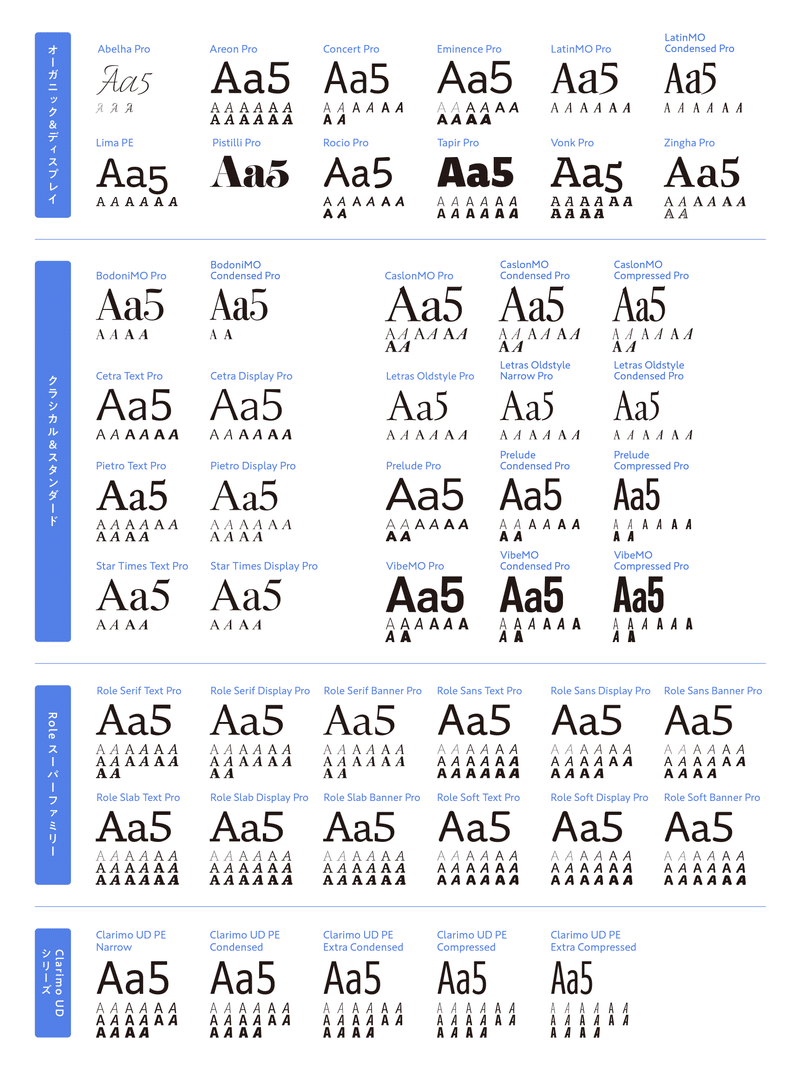
今年の欧文新書体を並べてみました。目を引く華やかな見出し書体からベーシックな書体まで、CondensedやCompressedなどの幅展開を含めるとこんなにたくさん……!
「Abelha Pro」や「Areon Pro」などのモリサワ タイプデザインコンペティションでの入賞作品や、アメリカで先行発売していた「Roleスーパーファミリー」も一挙リリースとなります。
ということで、ここからは個別の書体を詳しく見ていきましょう!
1. オーガニック&ディスプレイ
有機的なスタイルや、 見出し用途の強いインパクトを持つ書体をまとめたのが「オーガニック&ディスプレイ」。
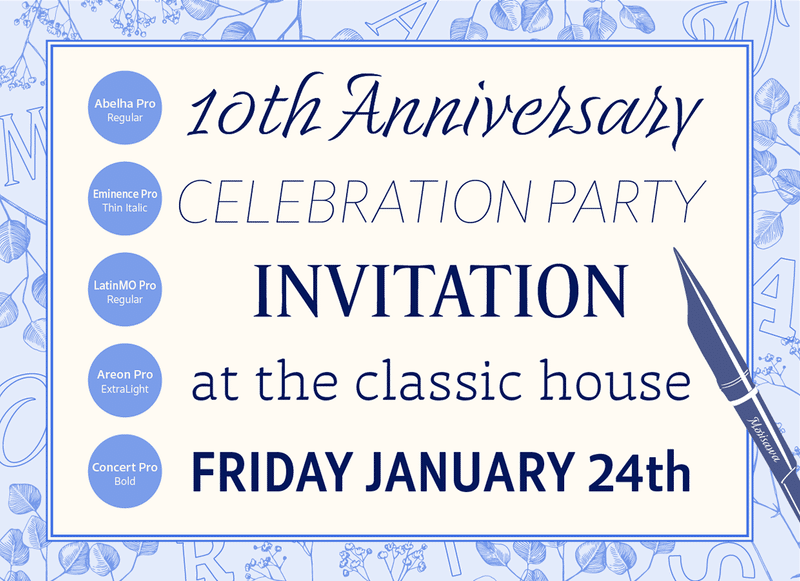
書体数が多いので、前後半に分けて画像にまとめてみました。
前半分は招待状をイメージしたワードで組んでいます!ほどよく丁寧でありながら、あたたかみも感じる書体が揃っています。
Abelha Pro
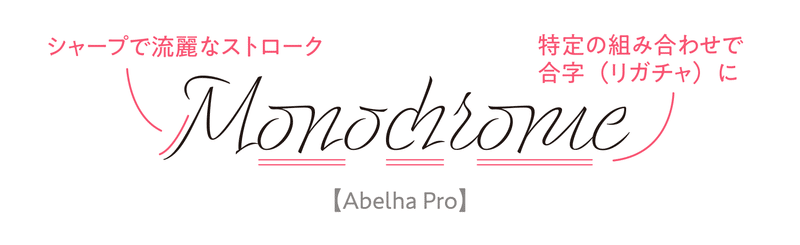
「Abelha Pro」は、書簡の筆跡を参考にデザインされたフォーマルな印象のスクリプト体です。シャープで流麗なストロークは、上品でありながらも軽やかな印象を与えます。
特定の組み合わせが来た際に置き換えとなる合字(リガチャ)にオリジナリティがあり、画像内「o・n」「c・h」「o・m」の組み合わせなどは、手書きだからこその合字だなと思います。
代替字形(オルタネイト)も多数搭載しているので、OpenType機能を使ってぜひお手元でいろんなパターンを試してみてください!
Areon Pro
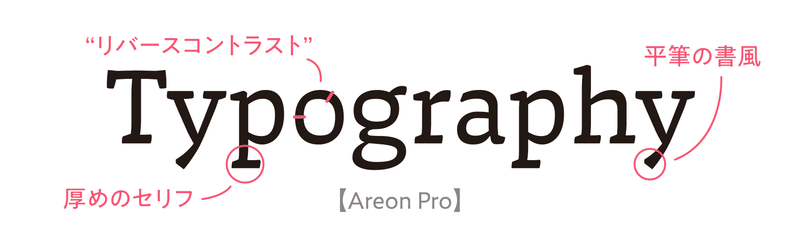
「Areon Pro」は、平筆の書風から着想を得た現代風のセリフ体です。“平筆の書風” というのは、例えば「y」の終筆に見られるような、平筆で書いた時の筆の角度によって太さが変わっているデザインのことを指しています。
セリフが厚めに設計されていることと、ややリバースぎみのコントラスト(太く描かれる部分と細く描かれる部分の関係性が逆転するデザイン)をもつことで、セリフ体でありながらどこか親しみやすさも感じます。
Concert Pro
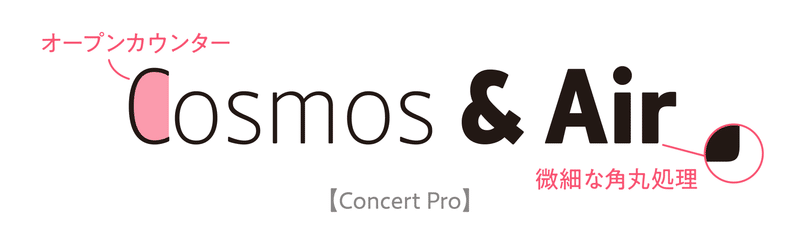
「Concert Pro」は、オンスクリーンでの利用を想定し開発されたやや長体ぎみのヒューマニスト・サンセリフ体です。
オープンカウンター(「C」などに見られる、文字の中に含まれる空間が開けていること)でシンプルな骨格であることに加え、ゆったりとしたスペーシングで設計されているため、可読性が高くなってます。
字幅の差が少なく文章を組んだ時に整理された印象をうけますが、アウトラインの先端に微細な角丸処理を施しているため、適度にあたたかみのある印象を与えることができる書体です。
Eminence Pro
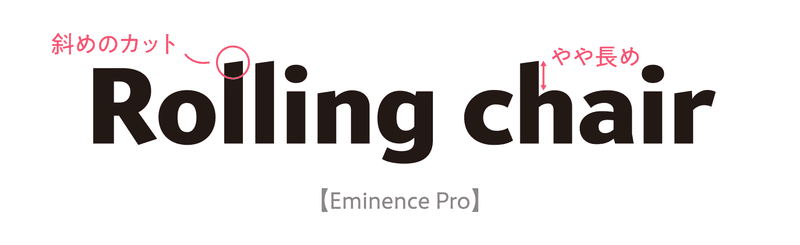
「Eminence Pro」はクリーンで明るい印象のサンセリフ体です。やや長めに設計されたアセンダー・ディセンダーラインが上品な印象を与えます。
画像内「l」(小文字のエル)の始筆に見られるような斜めのカットも特徴で、文章を組んだ際に心地よいリズム感が生まれます。ウエイトが上がるにつれカットの表情も色濃くなるので、細いウエイトで文章組みをし、太いウエイトを見出しで使った際にもしっかりメリハリを出すことができちゃいます!
LatinMO Pro / LatinMO Condensed Pro
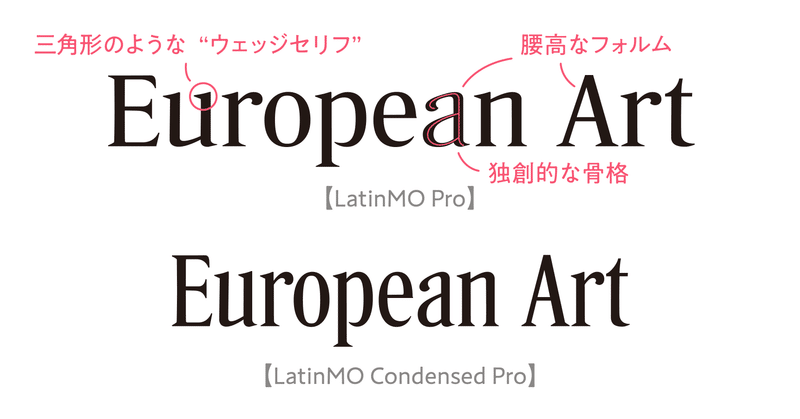
主に19世紀に見られた伝統的なウェッジセリフ体を再解釈したのが「LatinMO Pro」です。通常の字幅に加え、見出し利用に最適な長体のCondensedも用意されています。
“ウェッジセリフ” というのはなんぞや……という説明をしておきますと、“セリフ” というのは先端についた飾りのことで、それが三角形のような要素で構成されているのがウェッジセリフです。
この鋭利で繊細なセリフに腰高で独創的な骨格を合わせており、どこか気高さを感じさせるようなデザインになっています。伝記や歴史小説などの書籍装丁に合いそうな書体です。
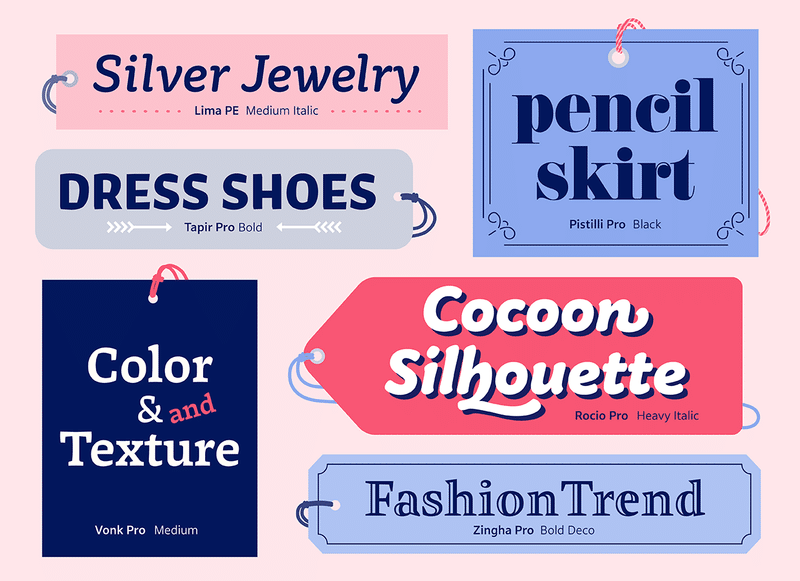
「オーガニック&ディスプレイ」の後半の書体たちを、ファッションをイメージしたワードで組んでみました!
デザイン性が高い書体が多く、和文組版のワンポイントアクセントとしてご利用いただくと華やかなニュアンスを演出できます。
Lima PE
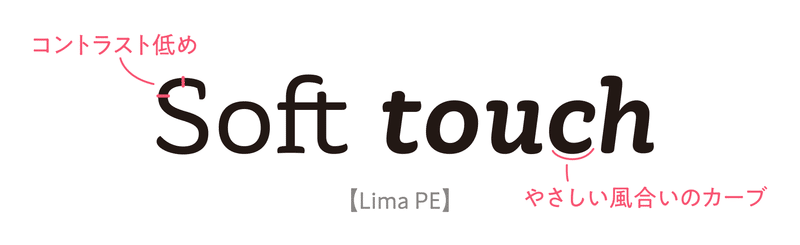
あたたかみのあるカジュアルな印象のセリフ体が「Lima PE」。
オンスクリーンの使用を想定して設計されており、アパーチャー(「S」や「c」などの文字の開口部)が広いことに加え、コントラストが低いので小さなサイズで使っても文字の輪郭が捉えやすく、本文組でも読みやすい書体です。
「c」に見られるような手書き由来のやわらかなカーブも、この書体のエッセンスになっています。
Pistilli Pro
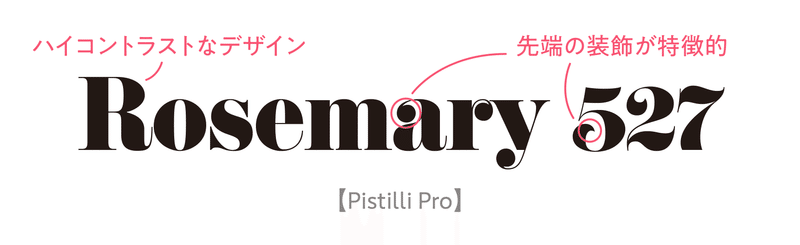
「Pistilli Pro」は、豪快さと繊細さを持ち合わせる見出し用のセリフ体です。コントラストが高く、先端のくるんとした装飾も特徴的で、かなりインパクトのあるデザインです。
雑誌やウェブサイトのタイトルや大見出しに使うことで、個性的かつオシャレ、という雰囲気を演出できちゃいます(個人的には数字のデザインが可愛くてイチオシです……!)。
Rocio Pro
どこか柔らかさを感じる画線で構成されているのが「Rocio Pro」。起筆・終筆部分に残るインクの溜まりのようなふくらみは、「Rocio」(スペイン語で「しずく」)の名にふさわしい、優しく豊かな印象を与えます。
Italicには装飾的なスワッシュ字形を多数搭載しており、単語の並びに合わせてデザインを置き替えることができちゃいます◎
グリーティングカードなどで華やかな印象が欲しい時に使えば、おしゃれになること間違いなし!
Tapir Pro
「Tapir Pro」は、太いマーカーペンで書いた文字の形から着想を得たサンセリフ体です。
「i」に見られるような端々のカットした処理や、「b」のように外側はなめらかな曲線に対して内側はエッジになっているところなど、遊び心のあるデザインになっています。少し重心が低めなのもポイントですね。
お菓子やおもちゃなどの子供向け商品のパッケージの見出しなど、ポップで明るい雰囲気を演出するのが得意な書体です。
Vonk Pro
「Vonk Pro」は、カリグラフィックな骨格に柔らかさと鋭さが混在するユニークなエレメントを採用した書体です。
分厚く無骨な印象のエレメントに対して、丁寧なスペーシングやカウンター(文字の中の空間)の設計を行っているため、小級数や低解像度のディスプレイ環境でも本文書体としての見やすさを失わないのが特徴です。
さきほどご紹介した「Rocio Pro」とこの「Vonk Pro」はリリース済みのフォントなのですが、ウエイトが大幅に拡充され、文字セットも100言語(Pro)に対応することとなりました。
より使いやすくなったこれらの書体を、ぜひ活かしてあげてください!
Zingha Pro
「Zingha Pro」は碑文に見られるようなカクカクとした処理と、エレガントでしなやかな骨格、という一見相反する要素を掛け合わせたデザインのセリフ体です。
Italicはよりカリグラフィックで独創的なデザインになっていたり、Boldには装飾的な白抜き処理を施した “Deco” というスタイルがあるなど、デザインのバリエーションが豊富なのも嬉しいポイントです。
2. クラシカル&スタンダード
「クラシカル&スタンダード」は、上品さを感じさせる伝統的なスタイルやシンプルで汎用性の高い書体をまとめています。
「オーガニック&ディスプレイ」と同様、2つに分けた前半の書体たちは、レストランのメニュー表をイメージして組んでみました。
全体的に安定感があるデザインですね(美味しいご飯が出てきそうです……)。
BodoniMO Pro / BodoniMO Condensed Pro
「BodoniMO Pro」は、上品で洗練された印象のモダン・ローマン体です。垂直に処理されたステム(縦画)やハイコントラストなデザインが、適度な緊張感とエレガントな表情を演出します。
通常の字幅とCondensedの幅展開があり、スペースが限られている場合はCondensedを使うことで可読性を保ちながらより多くの情報を表示できます◎
ちなみに、欧文に少し詳しい人なら必ず聞いたことがある「Bodoni」ですが、活字を元にした書体でして、各社からこれにインスパイアされた書体がリリースされています。
モリサワにも「本明朝-BOOK」という書体の専用欧文としての「Bodoni」がありますが、今回の「BodoniMO Pro」ともまた違ったデザインなんです。
いろいろなBodiniを比較してみるというのも “フォント沼” だと思うので、ぜひ見比べてみてください〜!
CaslonMO Pro / CaslonMO Condensed Pro / CaslonMO Compressed Pro
「CaslonMO Pro」は、Caslonの活字をベースにやや現代的に整理された書体で、オールド・ローマン(伝統的なデザイン)からモダン・ローマン(現代的なデザイン)の過渡期にあたるトランジショナル・ローマンに分類されます。この書体はCondensedとCompressedの2つの幅展開を持っています。
エレメントの先端が溶けたような丸みのあるニュアンスを持ち、太いウエイトになるほどその特徴が顕著になります。また、Italicになるとより上品さが増すのもポイントです!
Cetra Text Pro / Cetra Display Pro
「Cetra Text Pro」「Cetra Display Pro」はフィレンツェのルネサンス期碑文から着想を得た、ハイコントラストなサンセリフ体です。
“フレア” と言われる先端にかけて広がっていくようなエレメント形状からは、なんだかラグジュアリーな雰囲気を感じませんか?
6. あとがき